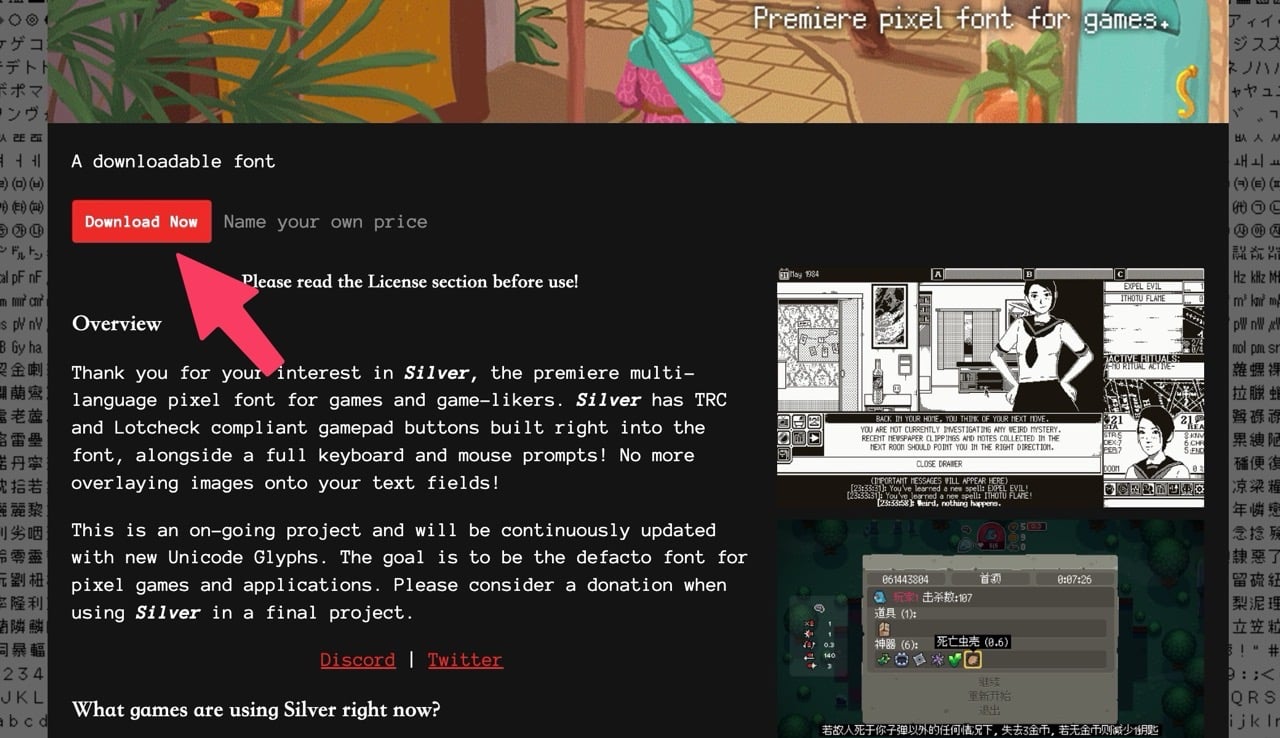
Silver:多語言點陣字型下載,適合遊戲與應用程式開發
Silver
Silver 是一個為遊戲和遊戲愛好者設計的多語言點陣字型,背後開發者為 Poppy Works,擁有符合 TRC(Technical Requirements Checklist)技術規範清單和 Lotcheck 審查標準的遊戲手把按鈕圖示,同時支援完整完整的鍵盤與滑鼠提示,在使用字型時無需額外加入圖片來顯示相關按鈕提示。
Silver 也是開放原始碼專案,並且不斷更新完善的 Unicode 字型,任何人都可以從官網免費下載使用。
下圖就是 Silver 實際呈現出來的效果,有一種早期老遊戲的感覺,在中文方面效果也很不錯,有興趣的朋友可以自行測試看看。
• Silver 字型支援 TRC 和 Lotcheck 審查標準,適用於遊戲 UI 設計
• 提供完整的鍵盤與滑鼠按鍵提示,不需額外製作圖片